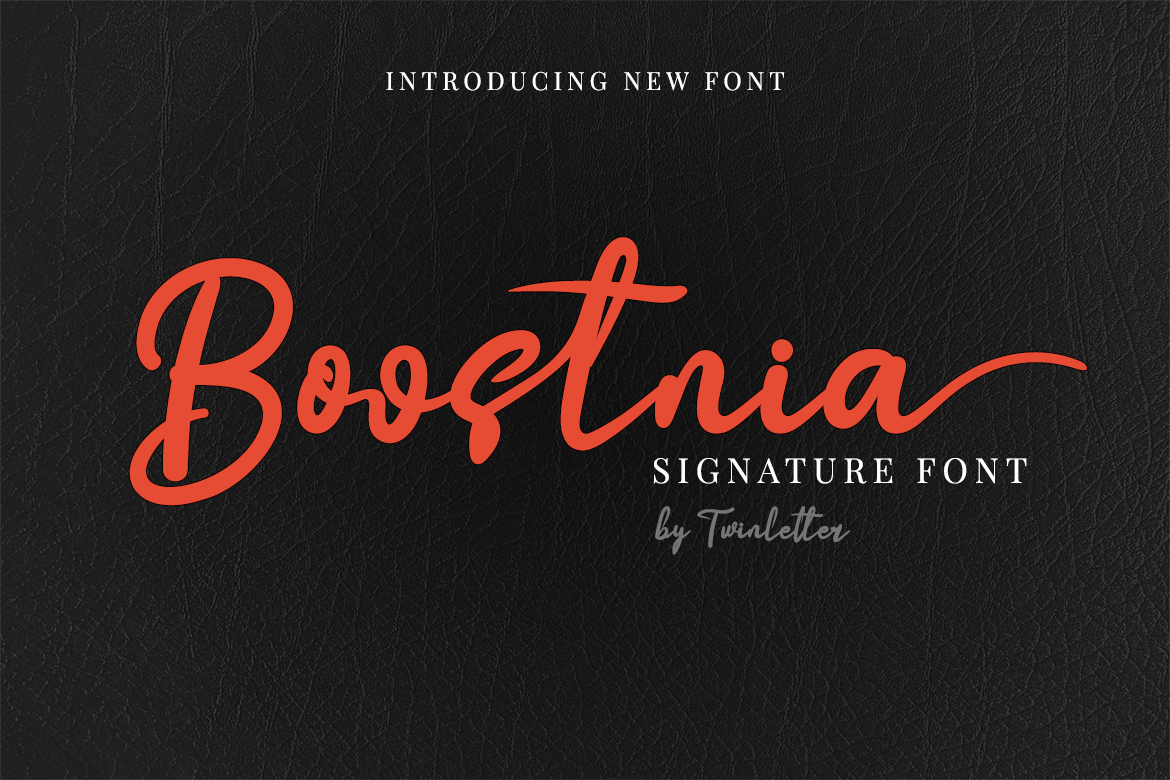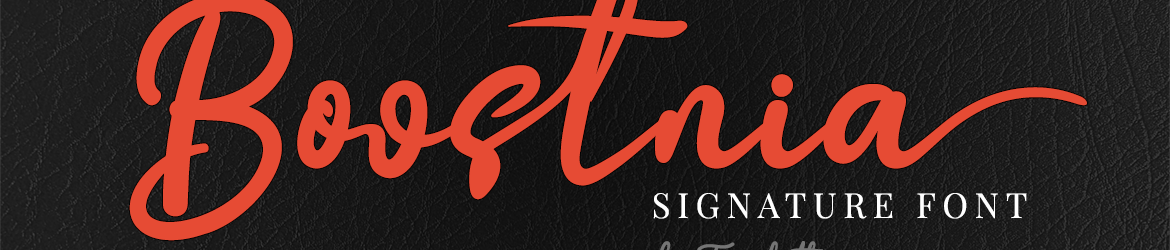
Esta é uma elegante fonte de script que transmite sofisticação e elegância. Com alternativas estilizadas e ligaturas criativas, Boostnia se ajusta perfeitamente para qualquer projeto. Suas características PUA (Propriedades Unicode Avançadas) permitem que você acesse facilmente todos os gílitos e swashes. Este recurso torna a fonte ainda mais versátil e permite uma grande flexibilidade no design, seja ela usada em editais profissionais ou em editoriais pessoais. Seja para um logo inovador ou um layout de site minimalista, Boostnia oferece as ferramentas necessárias para alcançar o resultado desejado com uma personalidade única e sofisticada.